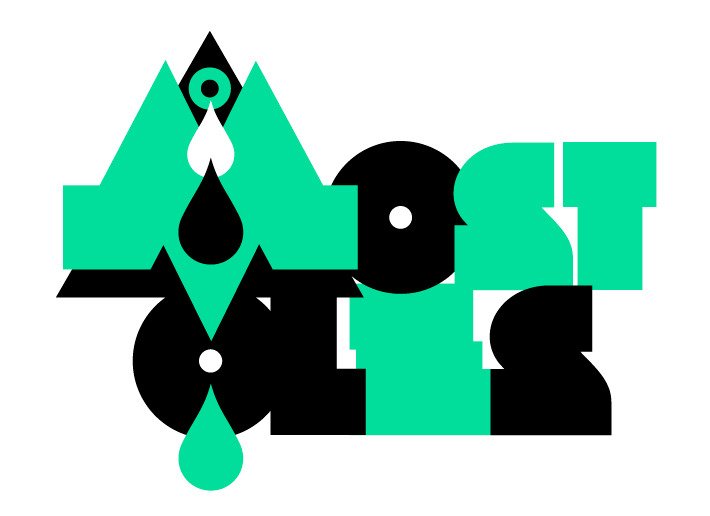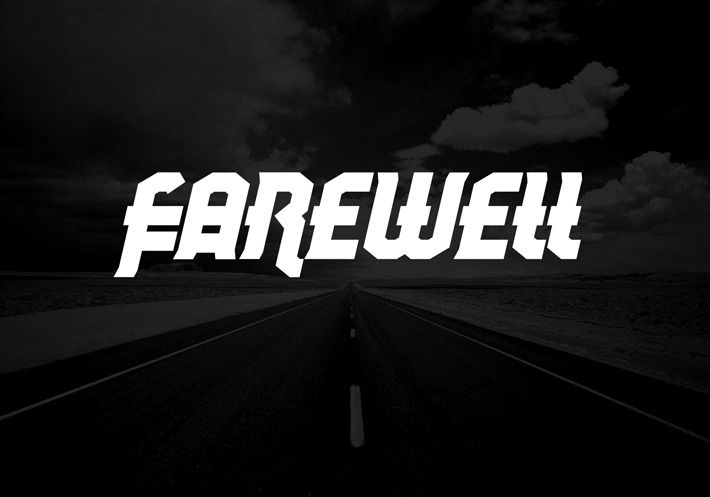
Talleres para resucitar la creatividad: tipografía modular y cómo convertir ideas en productos
Faltan 24 horas para la apertura del #ReebokCreativeHub, un espacio de creatividad temporal que estará en al corazón de Malasaña. Yorokobu también estará allí. El próximo lunes y el martes ofreceremos dos talleres gratuitos en colaboración con Reebok impartidos por Luis B, nuestro diseñador y director de arte, y Rafa Soto, director creativo de HerraizSoto y creador de Notegraphy.
Luis B impartirá un taller sobre tipografía modular para iniciarse en esta disciplina. En sus propias palabras: «En esta sesión conoceremos las pautas para crear alfabetos de carácter display y/o experimental. Jugaremos con la composición modular de una manera sencilla y versátil. Partiremos de módulos predefinidos y otros por definir para que los asistentes aprendan a construir letras y puedan generar sus propios alfabetos en el futuro».
Rafa Soto, en cambio, realizará un workshop sobre cómo convertir ideas en productos. El taller busca la manera de dar salida a esas ideas que se nos ocurren cada día. «Te encantan las ideas. Te acuestas con ellas, te las llevas de vinos, se te agolpan a la salida del cine y están de voz en off mientras tu tío te cuenta sus vacaciones. Pero la mayoría de las veces se quedan allí, en nada. Sin embargo convertir las ideas en productos es cada vez más fácil, estimulante y a lo mejor puedes incluso ganarte la vida con eso. Procesos, estrategias y “do’s and dont’s» para convertir algo que no existe en algo que existe. Cada equipo escogerá un producto relacionado con su afición (bicis, cámaras, cascos, fundas de portátil) y trabajaremos en la definición de producto y su salida al mundo».